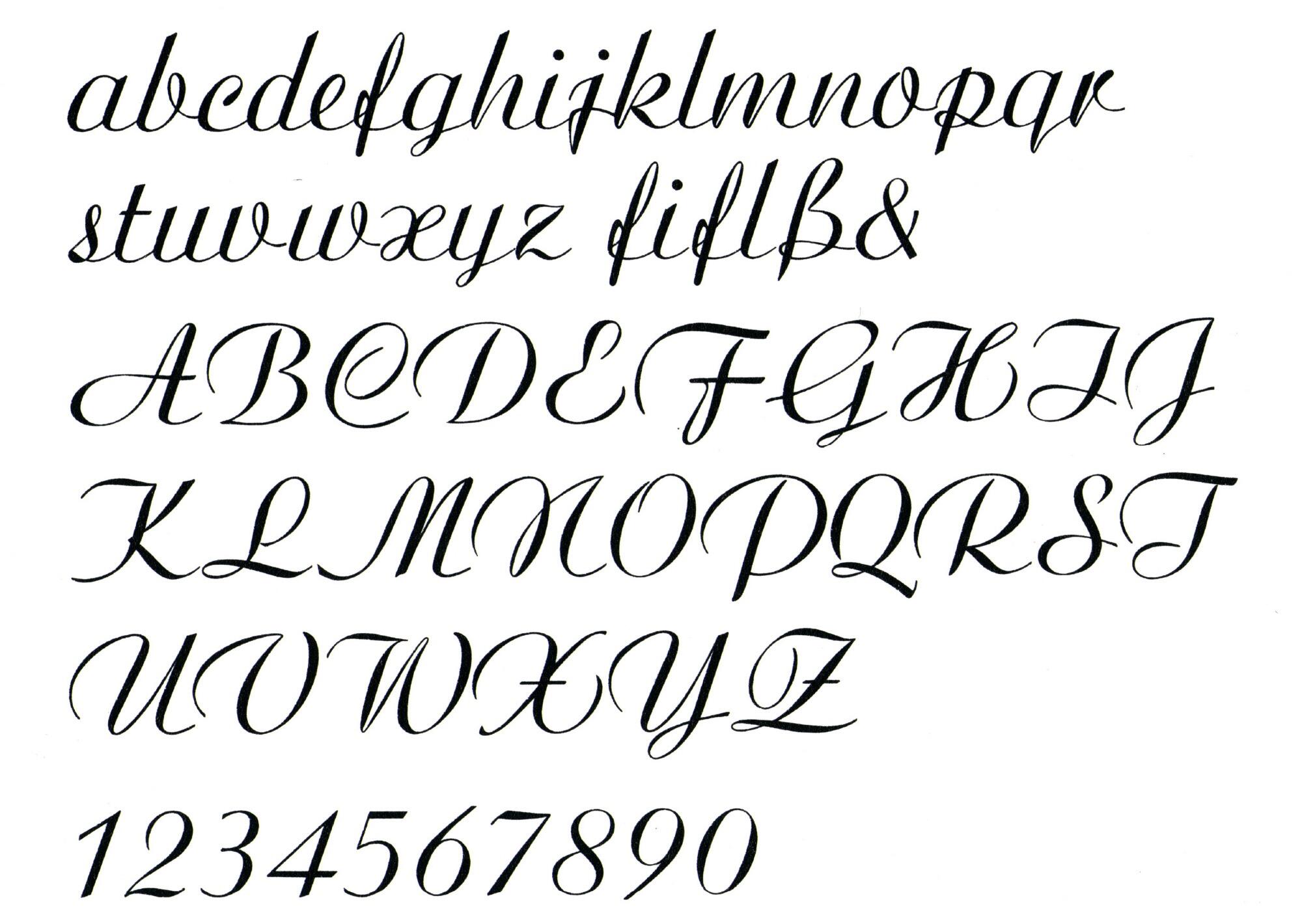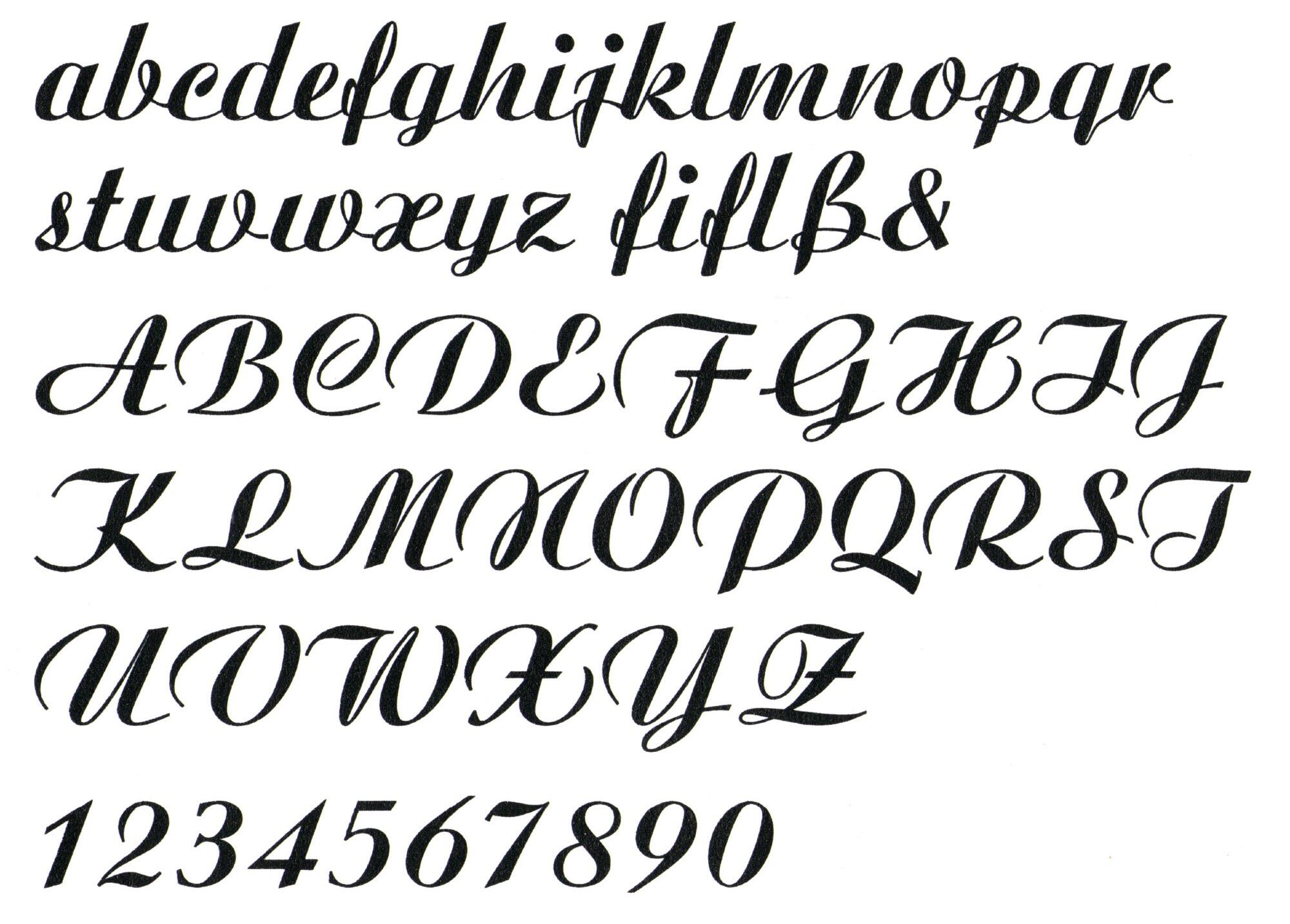
• 1933
• Antiqua Schreibschrift
Die Schreibschrift Ariston von Martin Wilke erschien ab 1932 bei der Berthold AG und wurde auf 3 Schnitte (normal, fett, extra) ausgebaut. Zum Zeichenvorrat gehörten einige Varianten für eine bessere Verbindung/Unterschneidung. Berthold bewarb die Schrift folgendermaßen: »Es gibt wohl kaum eine Schrift, die sich in so überzeugender Weise zunehmender Beliebtheit erfreut wie die Ariston. Zart und fließend in der Federführung zeigt sie jene unaufdringliche Eleganz, die für kultivierte Arbeiten immer gen gesehen ist.«